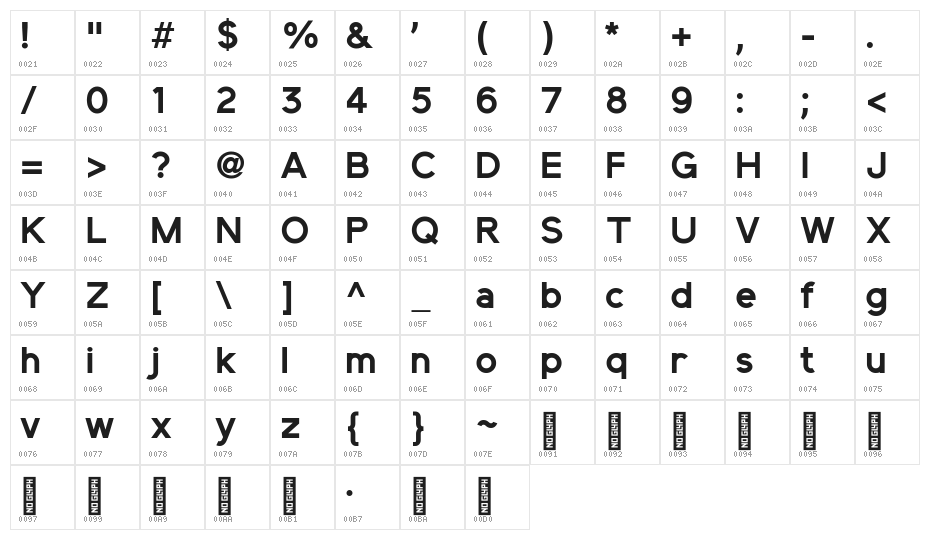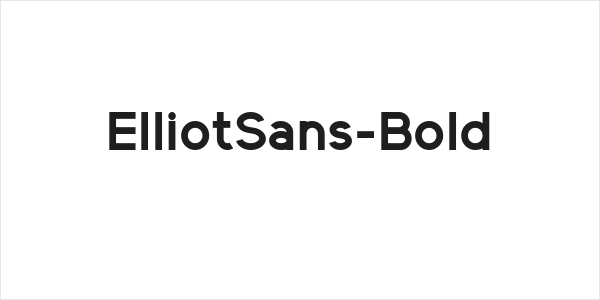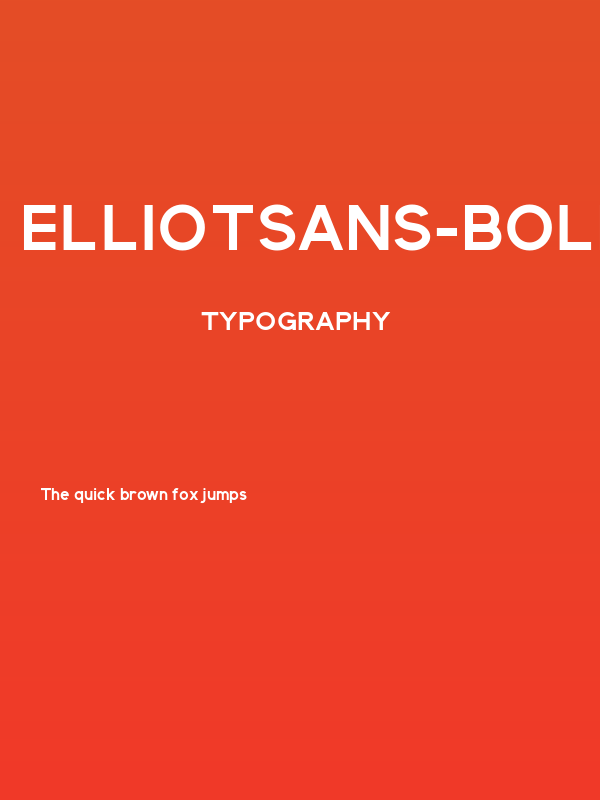
ElliotSans-Bold Font
✎ Sans Serif
| Anwendungsfall | Headlines, Logos, Digital Interfaces |
| Vorgeschlagene Projekte | Ideal for branding, headlines, posters, and digital interfaces where clarity and impact are essential. |